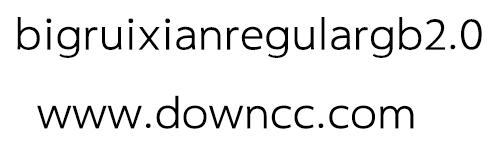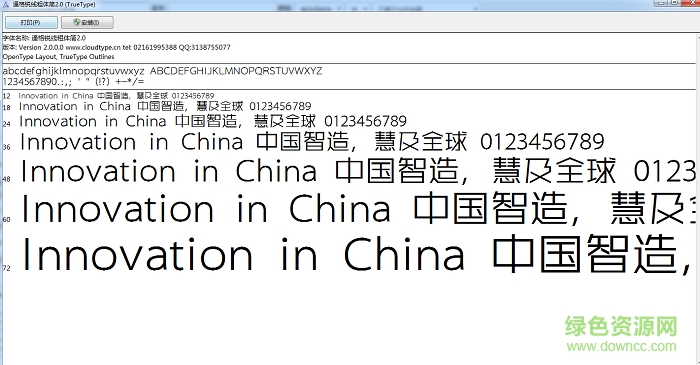
bigruixianregulargb2.0字體又叫逼格銳線粗體簡(jiǎn)2.0字體,是一款便于閱讀和識(shí)別的中文字體,該字體棱角突出,辨識(shí)度高,用在平面設(shè)計(jì)上有利益加強(qiáng)文字的特征,需要這款字體的小伙伴快來(lái)綠色資源網(wǎng)下載吧!